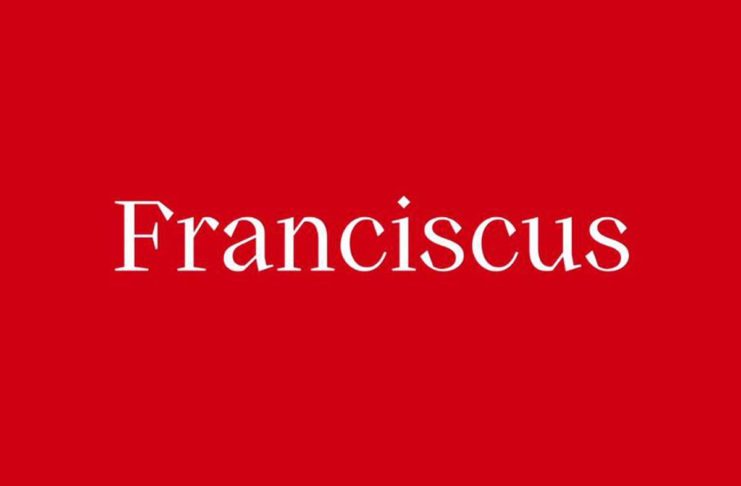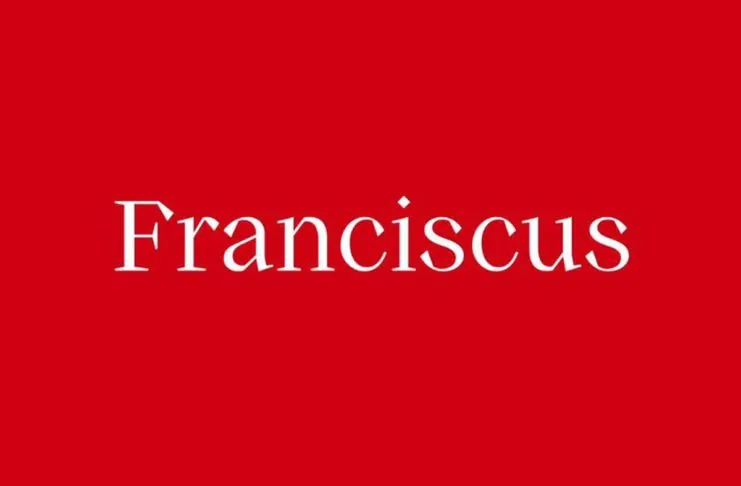
Franciscus, primo font digitale della Chiesa dai frati di Assisi
I frati del Sacro Convento di Assisi si preparano al centenario della rivista San Francesco e lo fanno varie novità, incluso un nuovo carattere tipografico. Il font in queatione – “Franciscus”, il primo font digitale della Chiesa, un unicum – è stato creato ad hoc, dai frati della Basilica di San Francesco e i designer di Studiogusto.
I frati fanno sapere he per elaborare il carattere sono stati fonte di ispirazione i manoscritti dal ‘200 al ‘400 della Biblioteca del Sacro Convento e gli affreschi della Basilica di San Francesco.
I tratti spigolosi, tipici della scrittura gotica medievale, sono stati il punto di partenza per la creazione di un carattere che mette insieme tradizione e contemporaneità. Franciscus, spiegano ancora i frati, affonda le radici nell’epoca di Francesco ma ha la forza di rivolgersi con chiarezza all’uomo di oggi. “Riflette l’identità francescana, capace di rinnovarsi sempre perché sempre attuale il messaggio del Santo di Assisi”. Franciscus sarà open source, scaricabile e disponibile gratuitamente per tutti.